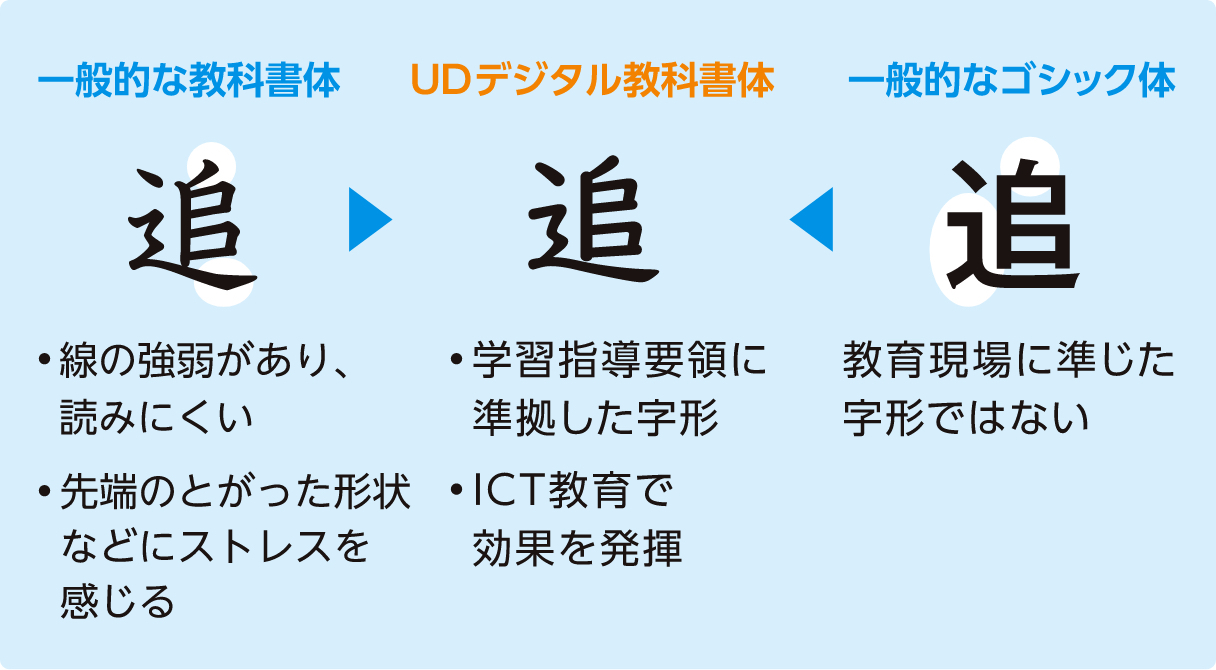
英語教育に最適な
UDフォントをご存知ですか?
2020年から小学生3年生から英語教育、小学5年生から英語の読み書きがスタートすることになりました。「UDデジタル教科書体 欧文シリーズ」はICT教育の現場に効果的なだけでなく、最新の学習指導要領に適した欧文もご用意しています。
UDデジタル教科書体 欧文の特徴
- 手の動きを重視した形状にする
- 鏡文字と間違えないように左右対象の形を避ける
- なるべく少ない画数で書ける
UDデジタル教科書体
書き学習用欧文で教員をサポート
アルファベットの書き学習で役立つ 「UD Digikyo Writing」
教科書・教材メーカー様や教職員のヒヤリングにより大文字・小文字の学習および指導がしやすいように文部科学省の英語教材の 4線比率(5:9:5)から(5:6:5)にリデザインした書き学習用の書体です。
「UD デジタル教科書体」のラインナップの欧文書体に、4線を重ねれば教材作成にも活用することができます。
書き学習のためには、大文字も学習しやすいUD Digikyo Writingをお勧めします。
※正体欧文の「UD DigiKyo Latin」、イタリック体の「UD DigiKyo Italic」も同様に4線を引くことが可能です。
新しい小学校英語での文字指導に適したUDデジタル教科書体の書き学習用欧文
「UDデジタル教科書体」とは?
モリサワは、教育の中で必要付加欠な「教科書体」をユニバーサルデザインに対応させた「UDデジタル教科書体」を開発しました。
- 硬筆やサインペンを意識し、手の動きを重視したデザイン
- ロービジョン(弱視)、ディスレクシア(読み書き障害)に配慮
ロービジョン(弱視)、ディスレクシア(読み書き障害)に配慮した教科書体を収録!
UDデジタル教科書体の検証
2019年に大阪医科大学LDセンター奥村智人氏が読み書きに困難さがある小学生2~6年生33人を対象として実施した検証では、読み速度が9%改善されることがわかりました。